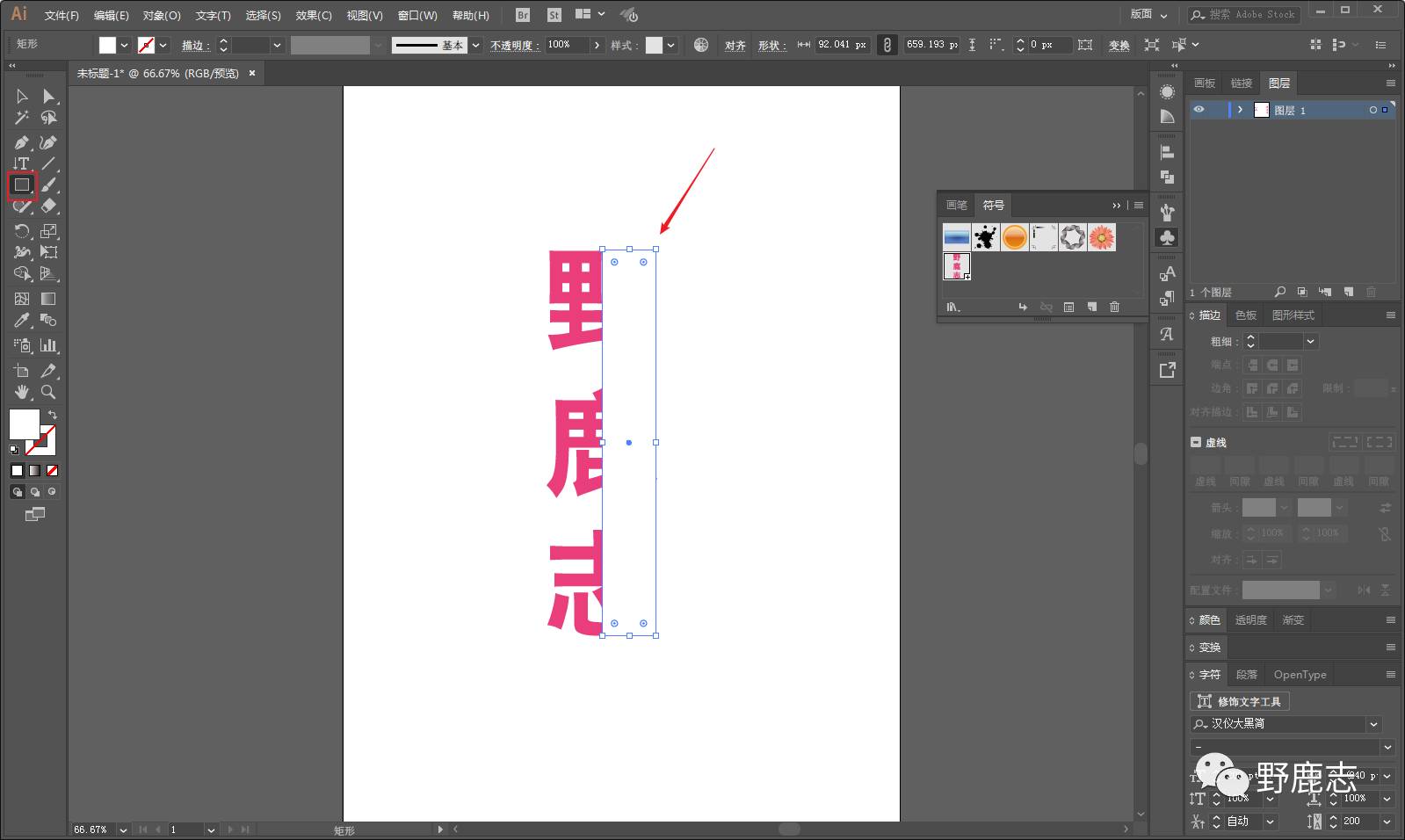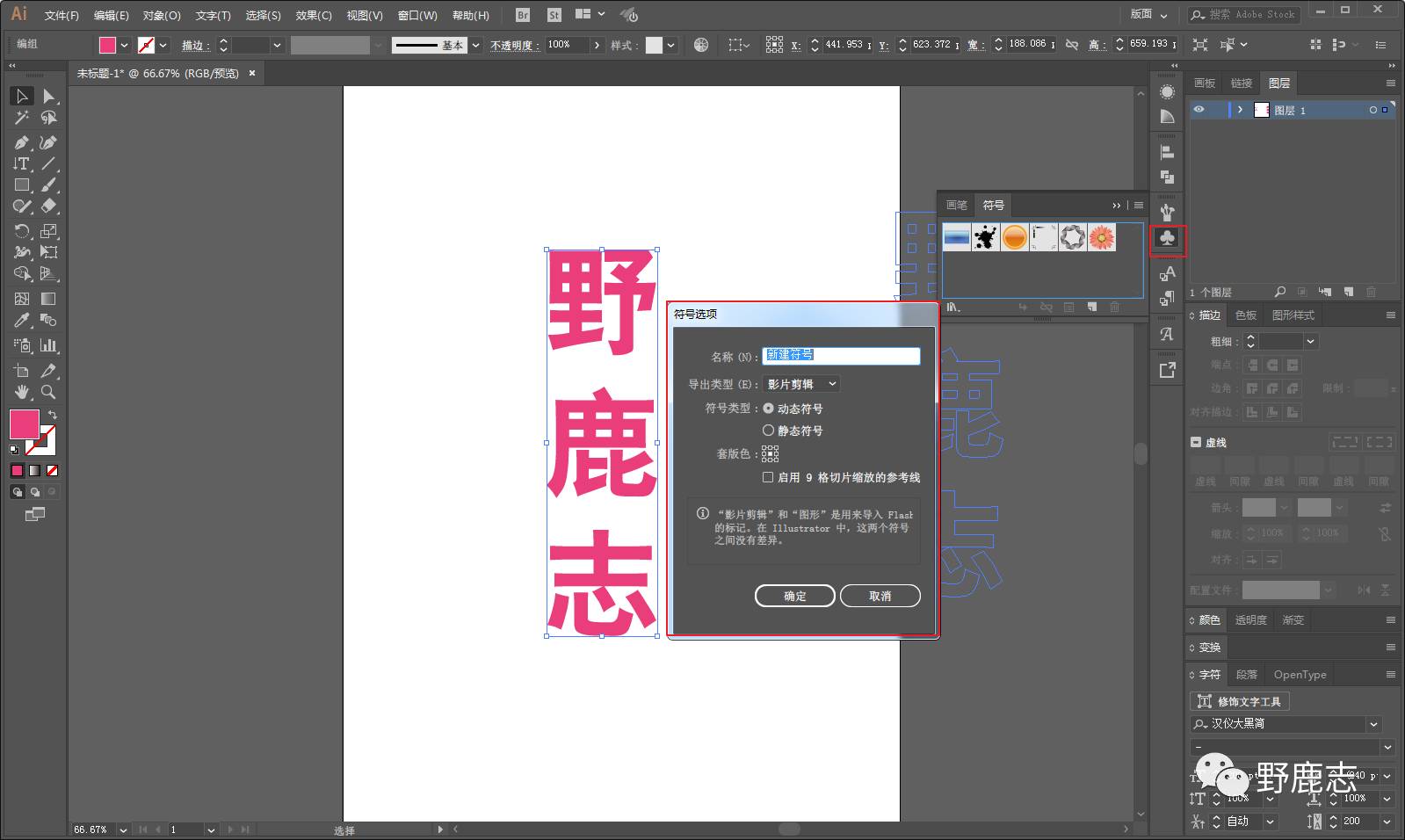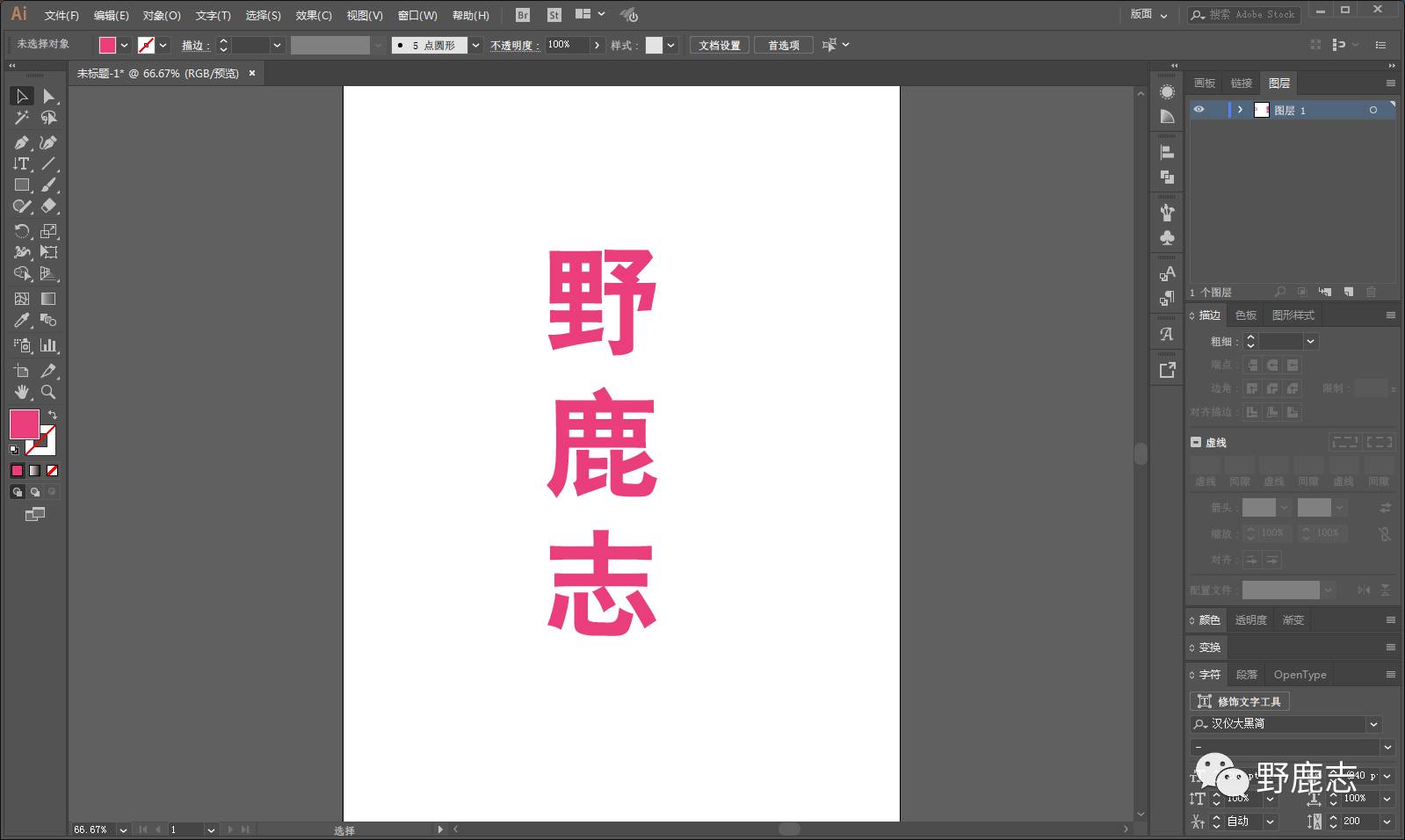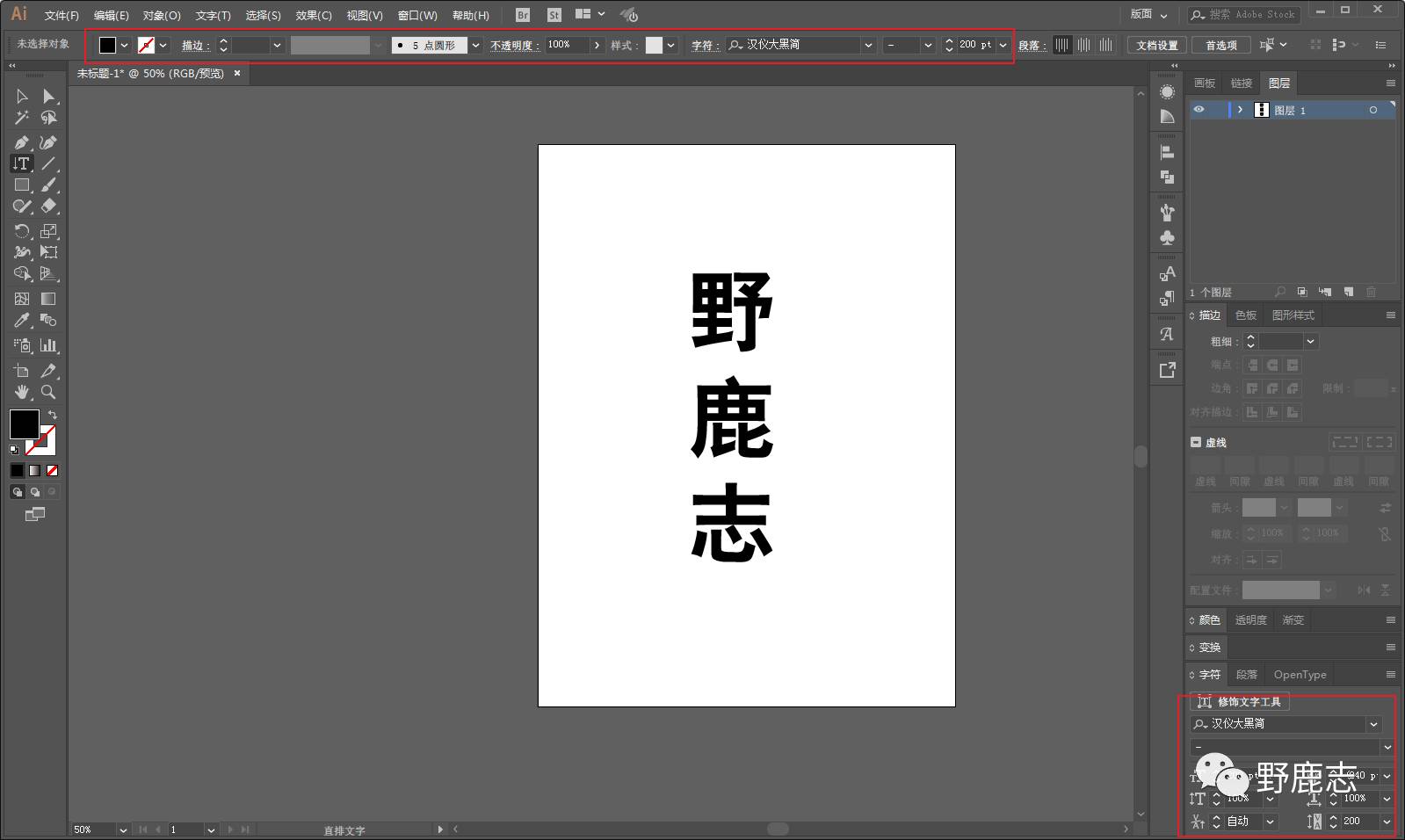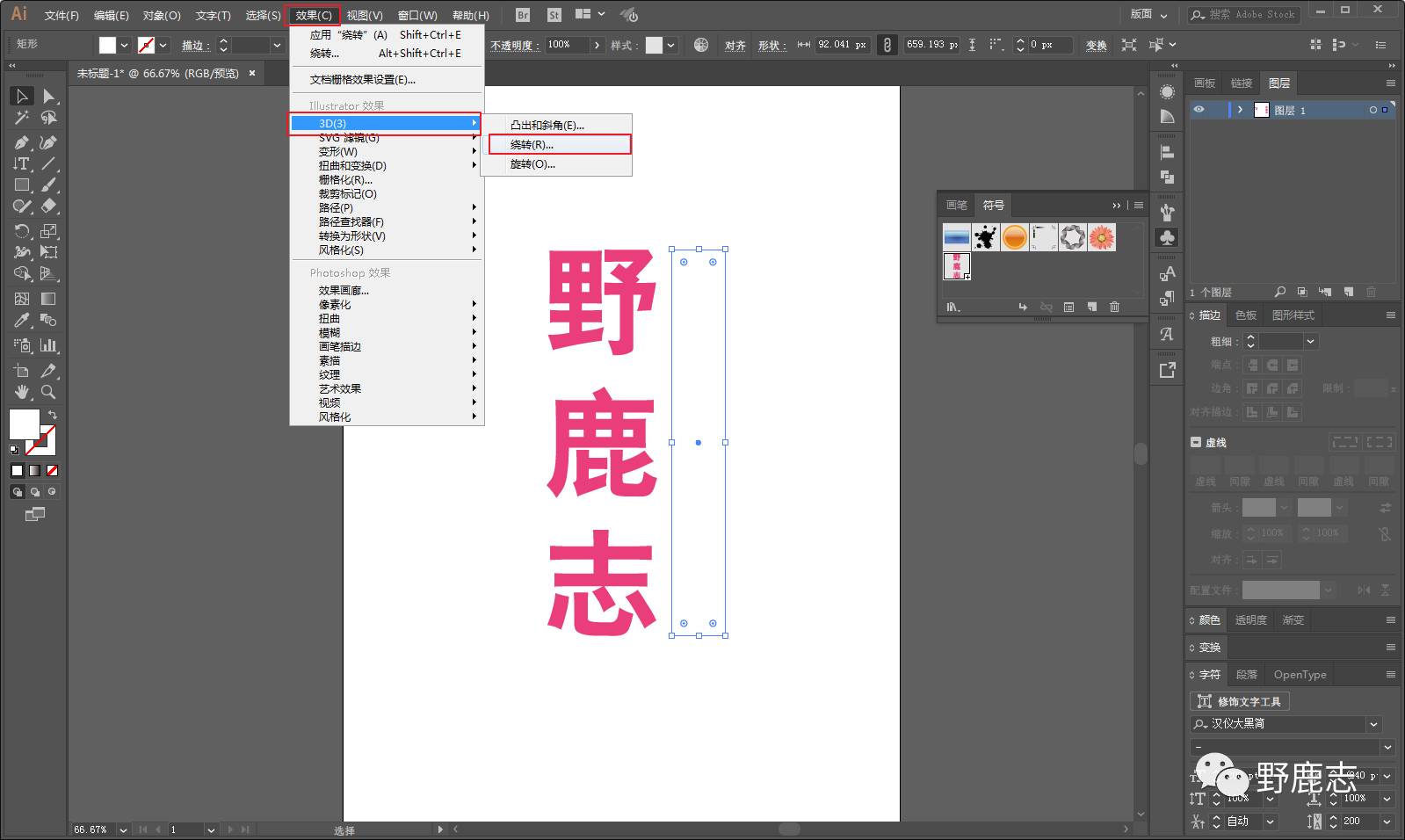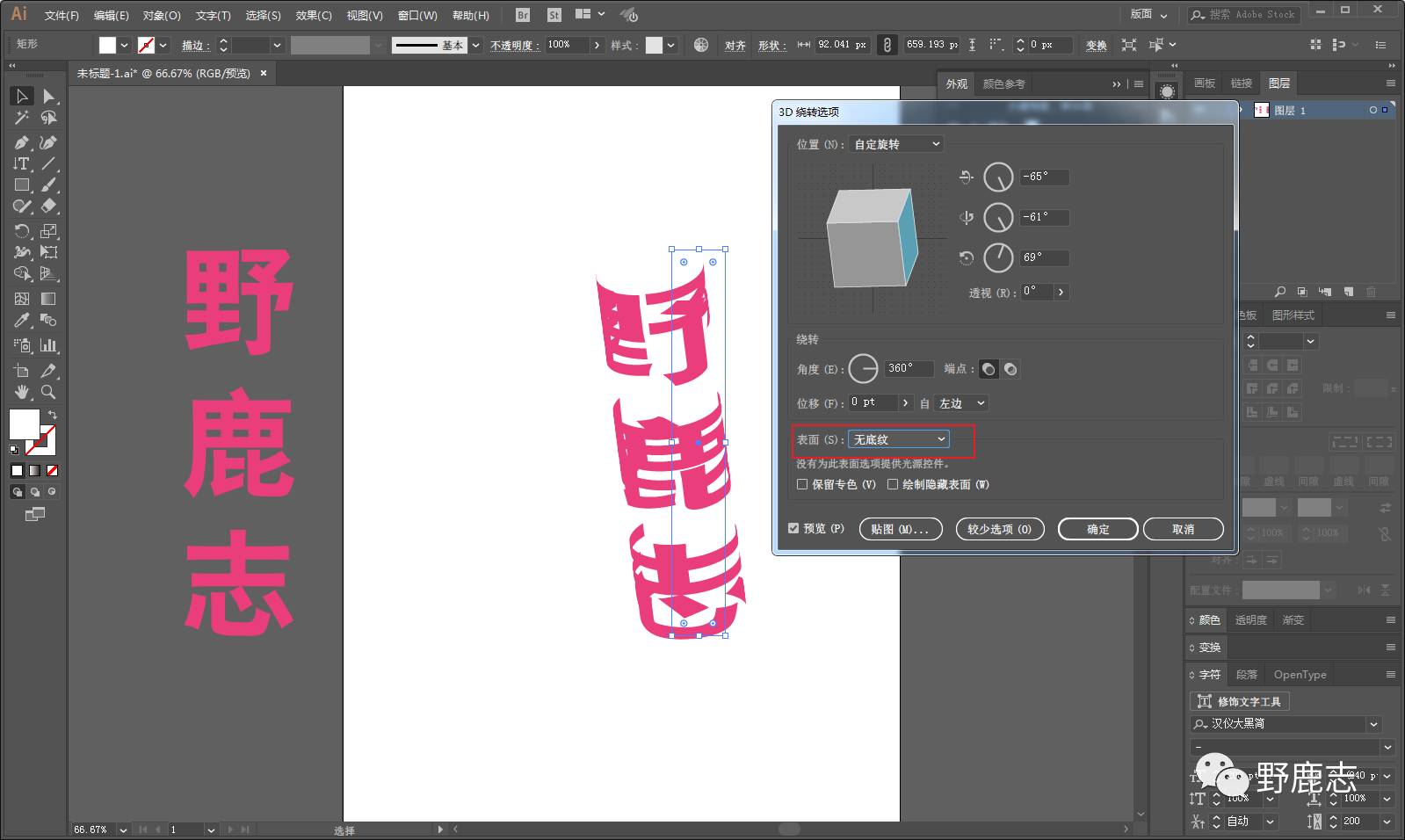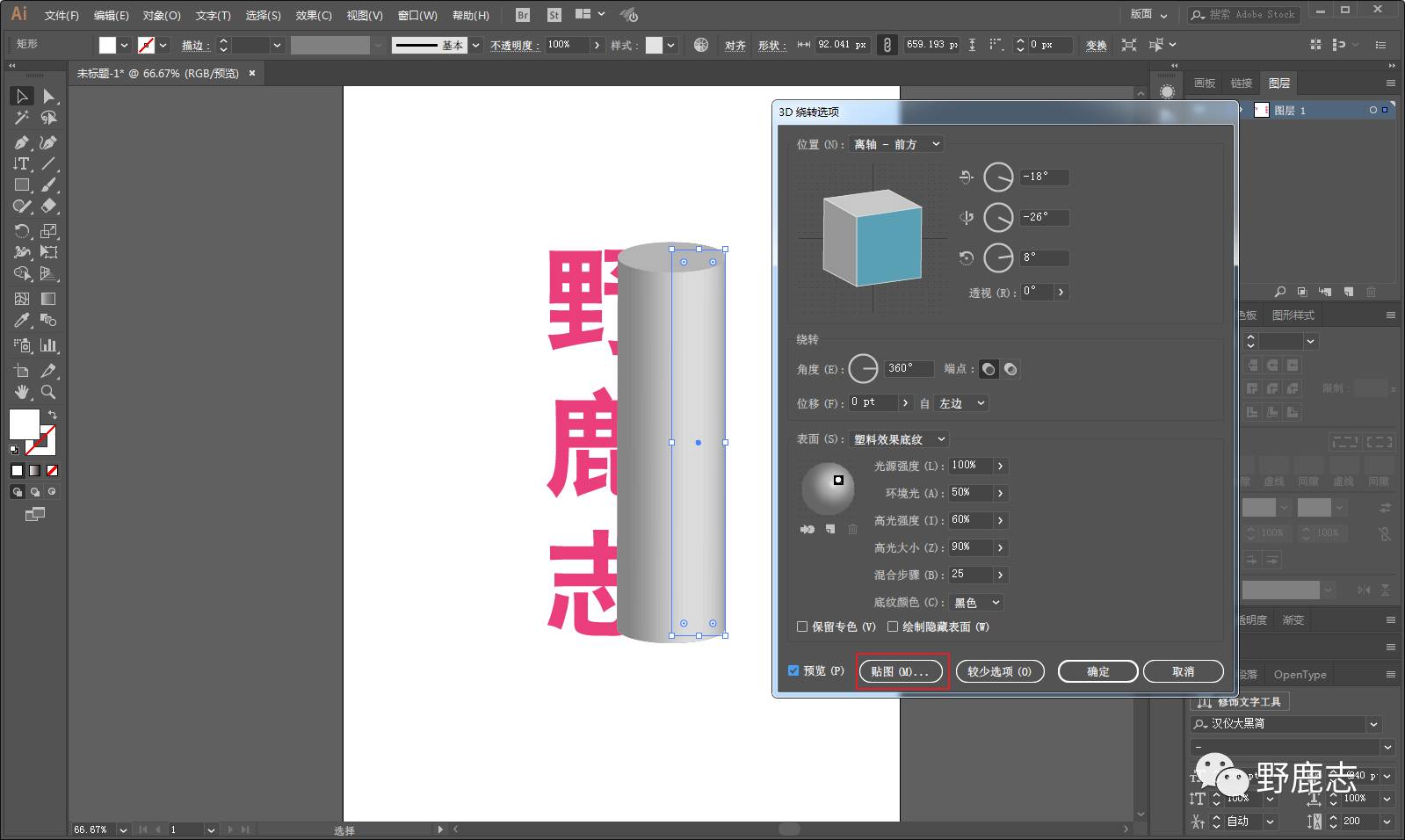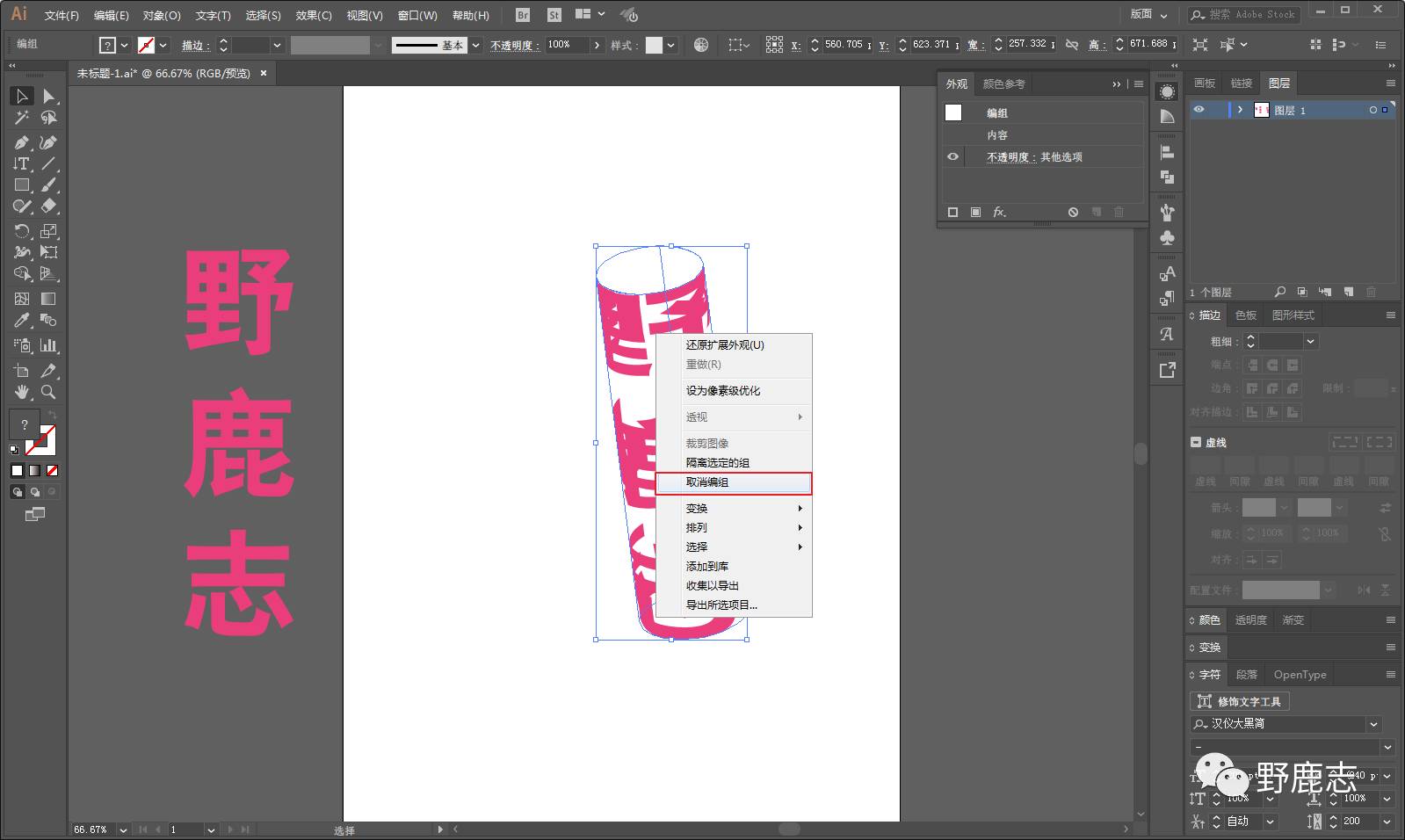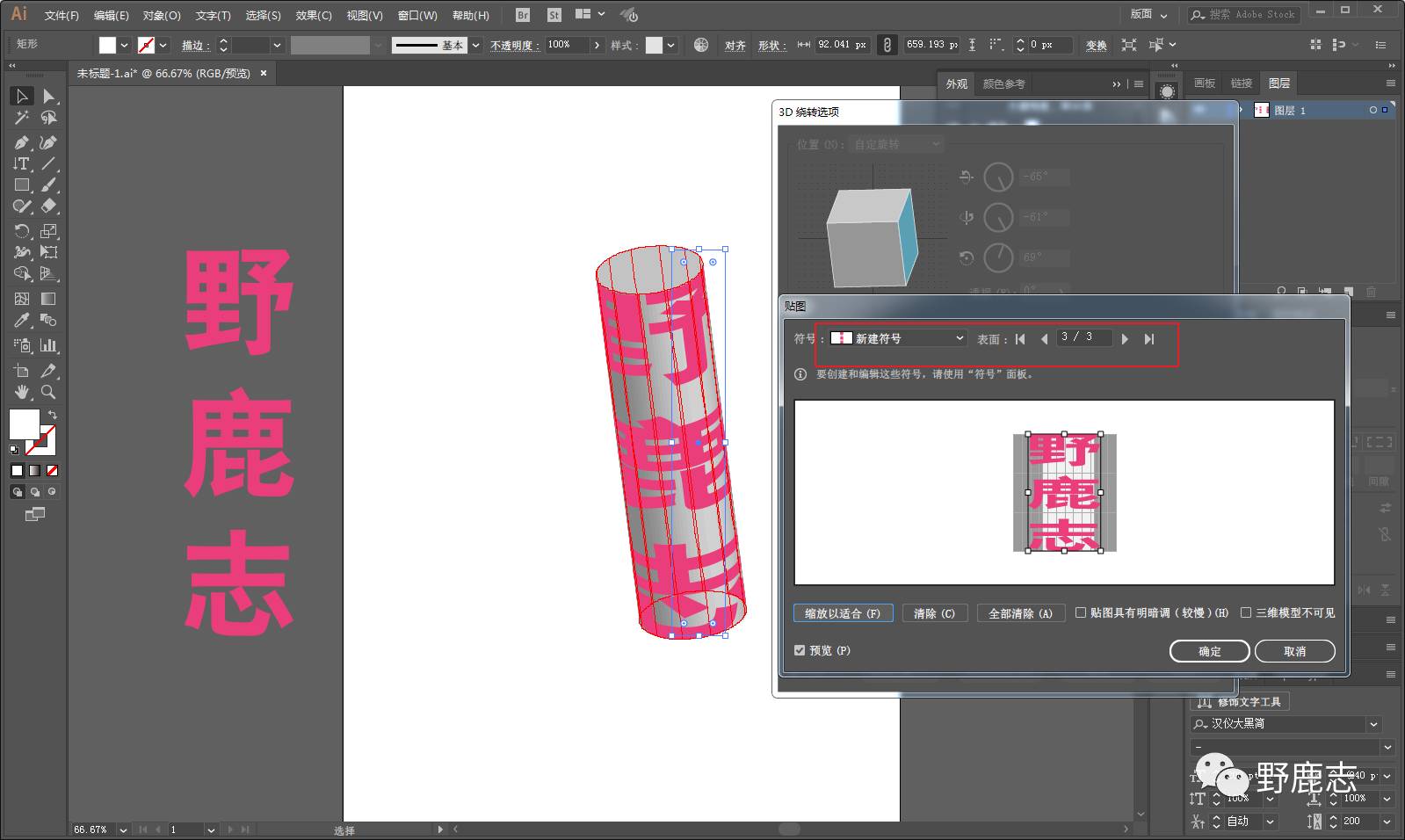
如何制作3D环绕文字海报,3D环绕文字海报制作方法分享
这个效果其实也是用到了Ai的3D贴图功能,很简单。
不过和之前的3D贴图不一样,用的是3D绕转,好啦,废话不多说,来一起制作这种立体环绕的文字海报吧!
首先打开Ai,新建画板,尺寸随意:
我这里先拿3个字来举例,打上文字,选择合适的字体,字号和间距大家看着办吧,合适就好:
修改颜色:
ctrl+shift+o轮廓化后,拖进符号面板,新建符号:
在文字的一半处画一个白色矩形,无描边。这样做的目的是为了后面贴图的大小更加合适:
接下来选中矩形,执行效果-3D-绕转:
其他参数别管,先点贴图:
贴图里,其他两个面不用贴,只贴侧面就可以了,然后再调整角度以及贴图的范围:
调整完毕以后,再将表面选择为无底纹:
接下来选中对象,执行对象-扩展外观:
鼠标右键取消编组:
再用小白工具,选中绕转的内侧部分,将填色的不透明度降低为50%左右,注意,一定是填色的不透明度噢:
将三个字的内侧颜色都修改完毕以后,再选中其中一个对象,执行选择-相同-填充颜色:
再对选中的对象统一添加描边:
这样一组文字基本上就搞好了:
其他的就不重复了,同样的方法,搞完大概这个样子:
最后还是码字排版导样机,老三套,看看效果吧:
嘛,字体的辨识度有待提高,不过基础方法大概是那样,开动脑筋再结合之前分享过的其他工具使用方法可以做出很多很棒的效果哦!